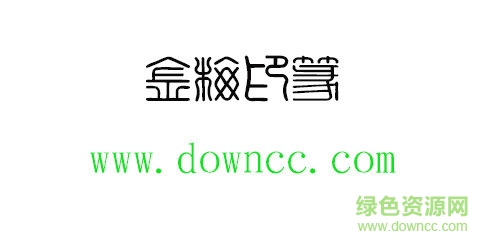
金梅印篆体字体
金梅印篆体字体是一款金梅类篆体字体软件,篆体字给人非常清晰高大上的感觉,而且此字体所变现的形式也非常具有特色,用户们也能用它来书写文字或者进行广告平面设计,实用又方便,感兴趣的用户就快来绿色资源网下载使用吧!
金梅印篆体是金梅字体中的一种类型的字体,它以古代文字的书写形式所表达的,能让你的文章也能表达出朴素的感觉,喜欢篆体字体的朋友可以下载使用看看效果如何。